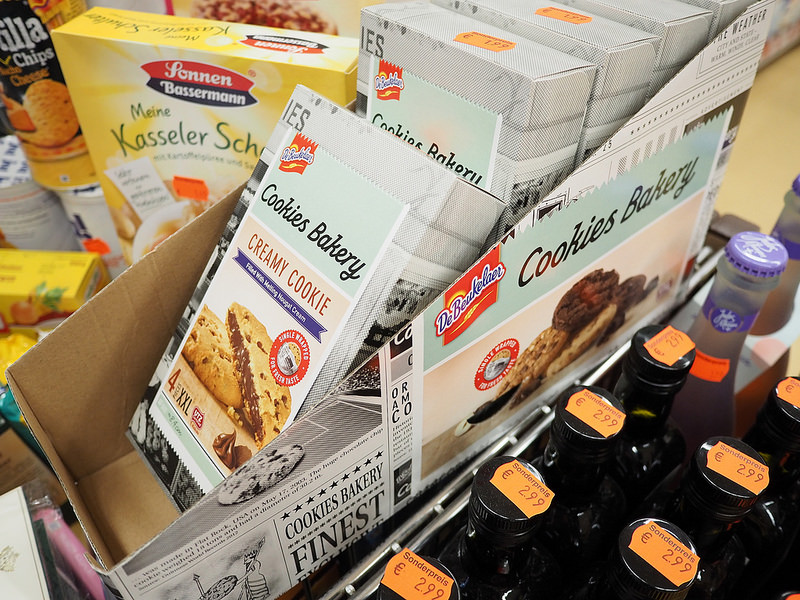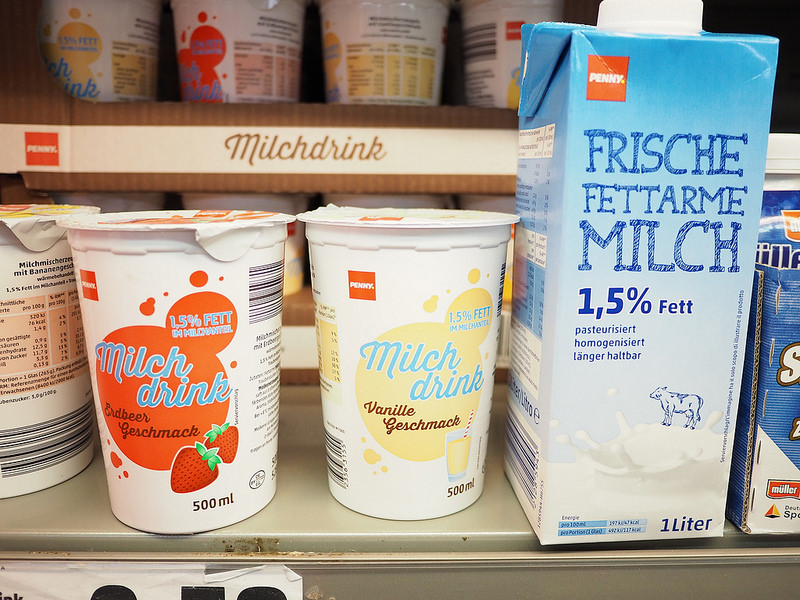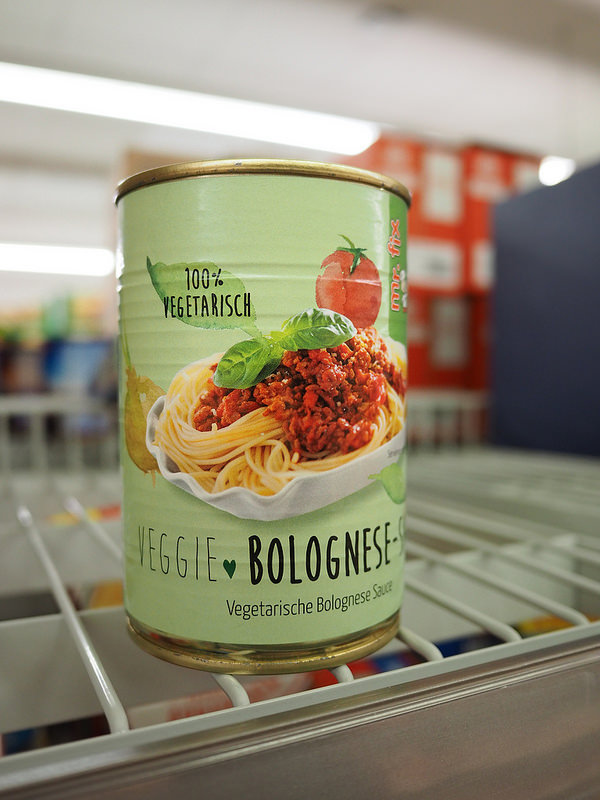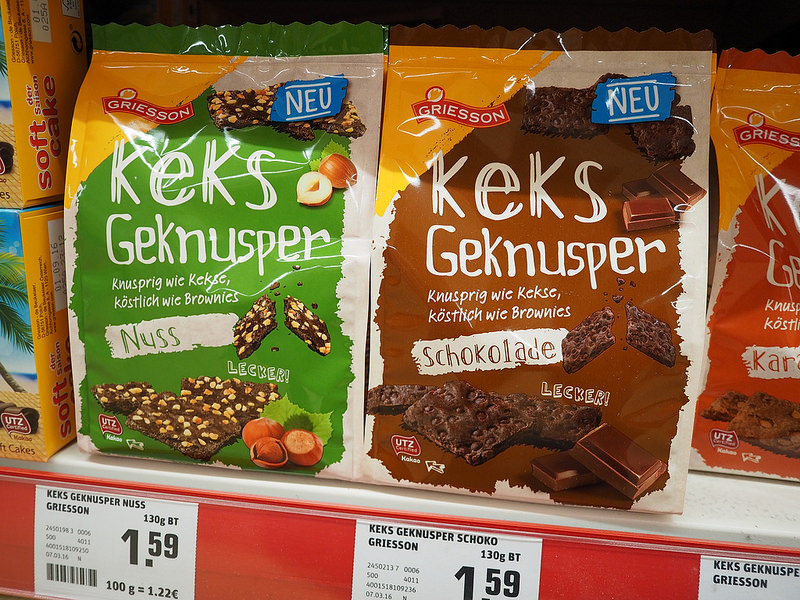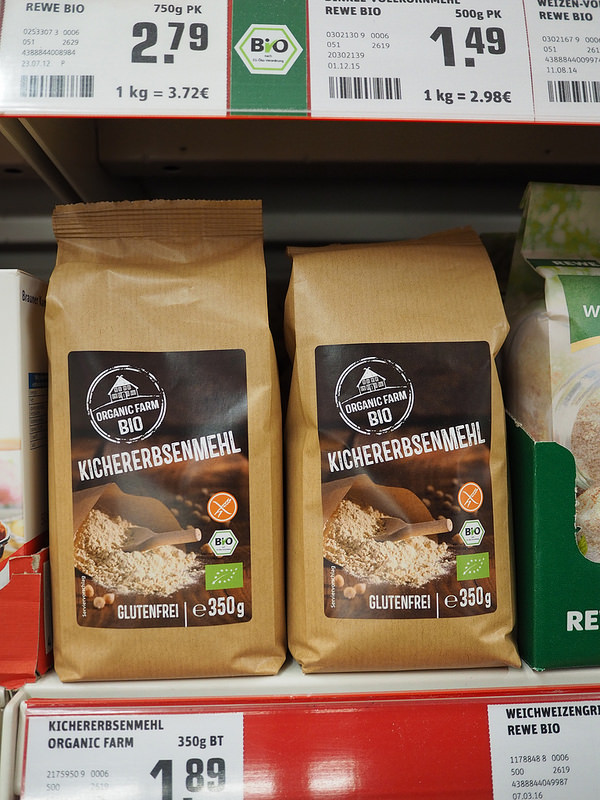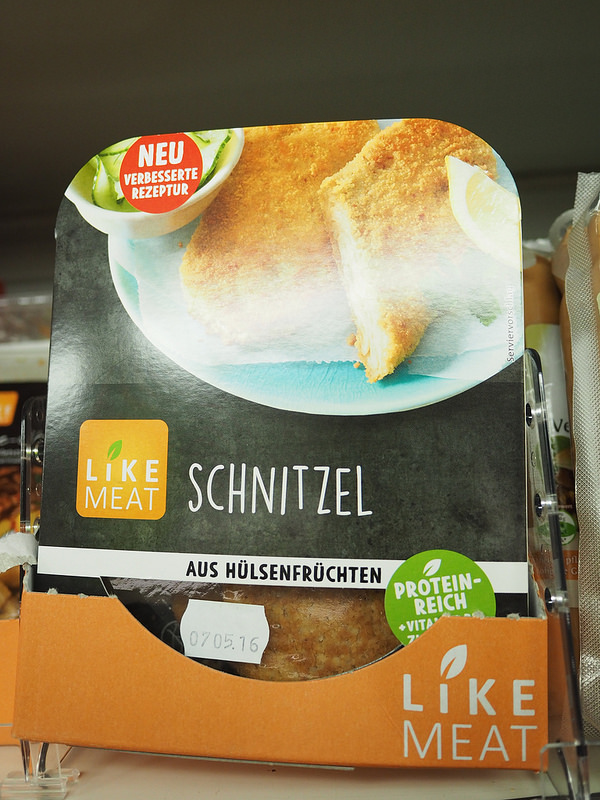
Modewelle: Condensed Comic-Schriften in All Caps und Small Caps für Nahrung, Gaststätten und Genuß (NGG)??
Zeitschriften, die gezielt mit solchen Schriften arbeiten: Good Health, Lecker, Mutti, … Dabei dürfte die Lecker im Hause Bauer damit angefangen haben, soweit ich mich entsinne.
Lecker von Bauer ist eindeutig NGG. Und die sind schon wieder runter vom Trip?
Good Health von Bauer ist nicht NGG. Aber meintest Du den Kopf als Handwerk? Der geht von meiner Frage weit weg.
Gleiches gilt auch für Mutti von Bauer ...
Ich meinte einen sehr speziellen Stil mit diese schmalen SC-AC-Markerschriften und sehr einfachen grafischen Basiselementen wie Kreise und Quadrate in Reinfarben. Das ganze wird dann in ein freundliches und leicht kindliches Design gesteckt.
bei der Lecker hat der Inhalt noch nie zum Titel gepasst
hab hier grad gesehn – ich hab ne BioSalatkiste vom Penny hier rumfahren -> Futura ... und einmal Apfelkompott -> Populaire ... auf dem Saft war die Brush Up usw. – ich seh da keine Tendenz zu einer speziellen Schriftgestaltung
Es ist ja im Grunde durchaus schlau, wenn auch zynisch und perfide, dass ausgerechnet Mammutunternehmen, die ziemlich mediokre (oder sagen wir's im Klartext: in vielen Fällen komplett minderwertige) Produkte massenhaft absetzen, Schriften einsetzen, die naive Unschuld suggerieren.
Nein, es ist keine Verschwörung, es ist einfach … Marktwirtschaft.
Es ist Propaganda/Werbung. Die Produkte sind Massenware und die Schriften haben eine genau gegenteilige Anmutung von Handwerk und -arbeit. Auf einer IIRC Nahkauf-Grafik habe ich da eine Pinselschrift gesehen. Diese war entweder echte Handarbeit oder hatte verschiedene Glyphen für die Buchstaben, ggf. kontextabhängig und als OTF-Feature. Das war erst vor einigen Tagen, als ich dies das erste Mal sah. Zur Zeit achte ich sehr darauf und es wäre unwahrscheinlich, dass ich dies übersehen hätte, so es mir schon mal vor die Augen gekommen wäre. Ach so, der Dönerladen schräg ggü. dem Nahkauf in KA-Südstadt am Werderplatz hat auch schon so eine Schrift in der Werbung (Stand Anfang April 2015) im Fenster.
Noch eine Anmerkung zu McD schiebe ich nach. Die dort verwendete Schrift passt zwar als Flachpinselschrift nicht zu den von mir hier genannten schmalen Marker-Schriften, aber das Prinzip dahinter ist das gleiche: Fließbandprodukten Assoziationen mit Handarbeit zu verpassen. Ähnliche Schriften dieser Art wären Cantoni und Bonjour als fette sowie Bombshell und Florabella als etwas dünnere Schriften.
Cantoni
Bombshell
Florabella
Angefangen hat diese Modewelle wohl 2012/2013 ganz dezent, dann wurde Mai 2015 Creativ Market mit solchen Schriften überschwemmt ... Die Verfügbarkeit stieg damit rasant an. Dieses Stadium hatten die schmalen Markerschriften schon spätestens 2012 und 2014 gab es massige CC und SIL-OFL-Schriften. Beim Schriftenhörnchen findet man die unter Handdrawn. Aber wie sieht es mit den Flachpnselschriften aus? Eher mau. Hier aber was freies, nicht ganz die Richtung, aber fast: Landliebe von Richard Mitchell aus dem Jahr 2009:
Das könnte auf einen gleitenden Übergang von diesen schmalen Markerschriften auf diese Flachpinselschriften hindeuten? Preiswert verfügbare Bundle zusammen mit anderen handwerklichen Schriften werden zu niedrigen Preisen auf den Markt geworfen. Schaun wir mal wie sich das entwickeln wird. *grübel* Dann wäre McD eher Vorreiter als Trittbrettfahrer?
bei der Lecker hat der Inhalt noch nie zum Titel gepasst
hab hier grad gesehn – ich hab ne BioSalatkiste vom Penny hier rumfahren -> Futura ... und einmal Apfelkompott -> Populaire ... auf dem Saft war die Brush Up usw. – ich seh da keine Tendenz zu einer speziellen Schriftgestaltung
So gesehen ist das fast korrekt. Ok, Antiqua sind eher selten und die Serifen bleiben einem entweder im Hals stecken oder kratzen höllisch beim Runterschlucken. Daher findet man Antiqua nur sehr selten im Bereich NGG und dann meistens für ausgewählte Produkte wie Alkoholika. Aber Du blickst aus der falschen Richtung für diese Zuordnung. Ich habe nicht die Produkte angesehen und versucht dann eine Zuordnung zu den Schriften vorzunehmen. Ich habe die Schriften angesehen und diese dann den Produkten zugeordnet und bin dabei auf ein Schema gestoßen. Ist der Unterschied in der Betrachtungsweise klar? Und kannst Du Dir auch vorstellen warum Dein Ansatz idR nicht funktionieren kann um solche Schemen zu finden? Örghs ... wie beschreibt man so was in klaren Worten ohne Mathematik? Und wie beschreibt man das mit Mathematik? Es tut mir da ein bisschen leid, aber ich habe ein viertel Jahrhundert Übung, davon über ein Jahrzehnt Bildverarbeitung und Mustererkennung, in solchen Denkweisen und das geht bei mir fast schon unterbewusst ab. Ist halt Mustererkennung auf einer anderen Ebene …
und aus dem Altpapier:
gibt aber auch andere Tendenzen – komplett clean z.B.:
usw.